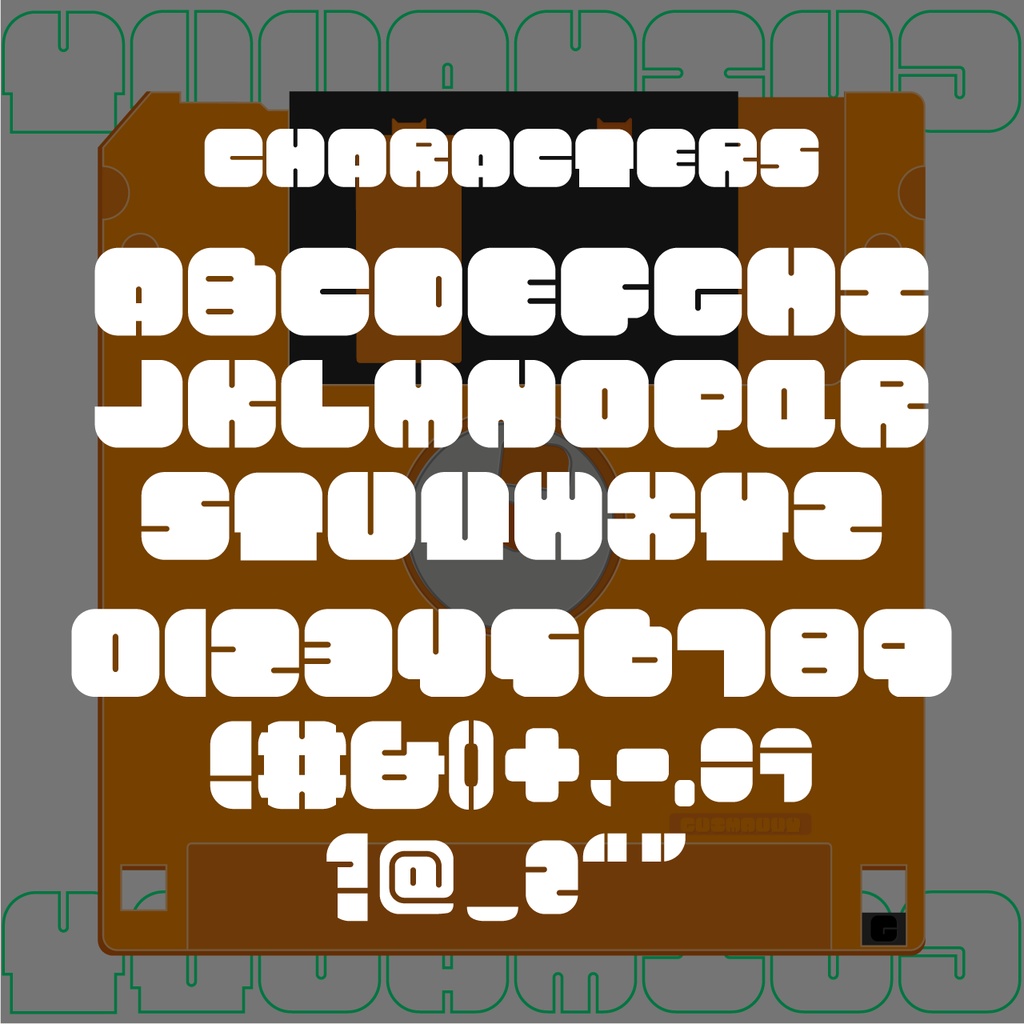
【無料】GUIMAUVY【フォント】
-GUIMAUVY- ・ギモーヴィと読みます ・とても太い塊のようなフォントです。 ・庶民用、富豪用、大富豪用、石油王用に違いはありません。製作者が喜ぶだけです。我こそは富豪なりという方は是非。 ------------------------------------- ○収録文字○ ABCDEFGHIJKLMNOPQRSTUVWXYZ &@_(),.;:“”~#+-!? 0123456789 ------------------------------------- ○使用について○ ・個人/商用利用を問わず、自由に無料で使用できます。(Twitterなどで教えてくれると嬉しい) ・同人誌等で使用した場合、奥付でここのURLを掲載していただければうれしいです。(しなくてもいいよ) ・改変や派生フォントの作成、ファイル、ソフトウェア、Webページへの組み込みも可能です。 ・改変/派生フォントの販売可 ※報告必須。宣伝させてね。 ○注意事項○ ・全ての環境で正常に動作する保証はできかねます。また、当フォントを利用したことによって発生した故障、損害についても責任を負わないこととします。 ・再配布、製作者を名乗るのは禁止です。 ○zipファイル内容物○ GUIMAUVY.eot GUIMAUVY.ttf GUIMAUVY.woff readme_yondene-.txt 製作者Twitter https://twitter.com/Zm_VCD Twitterにアクセスできない人向け連絡先 rendarak.cave❖gmail.com ----- ↓English below↓----- -GUIMAUVY- - Pronounced “Guimauvi” — like the fluffy French sweet guimauve. - A super chunky, blocky font. - No difference between the versions for commoners, millionaires, billionaires, or oil tycoons. Only the creator’s happiness increases. If you consider yourself wealthy, why not give it a try? ○ About Usage ○ - Free to use for both personal and commercial purposes. (Let me know on Twitter if you do—I'd love to see it!) - If used in doujin works or publications, I’d appreciate it if you credit the URL on the colophon. (Not mandatory though!) - You’re welcome to modify the font, create derivatives, or embed it into files, software, or web pages. - Commercial sales of modified or derivative fonts are allowed—just make sure to report it to me. Just let me know — I’d love to help promote it! ○ Disclaimer ○ - I cannot guarantee it will work perfectly in all environments. - I'm not responsible for any damages or issues that may occur from using this font. - Redistribution or claiming to be the original creator is strictly prohibited. -+-+-+-+-+-+-+-+-+-+-+-+-+-+-+-+-+-+-+-+ ○ characters ○ ABCDEFGHIJKLMNOPQRSTUVWXYZ &@_(),.;:“”~#+-!? 0123456789 -+-+-+-+-+-+-+-+-+-+-+-+-+-+-+-+-+-+-+-+ ○ZIP File Contents○ GUIMAUVY.eot GUIMAUVY.ttf GUIMAUVY.woff readme_yondene-.txt creatorTwitter https://twitter.com/Zm_VCD Can’t reach me on Twitter? Try here! rendarak.cave❖gmail.com